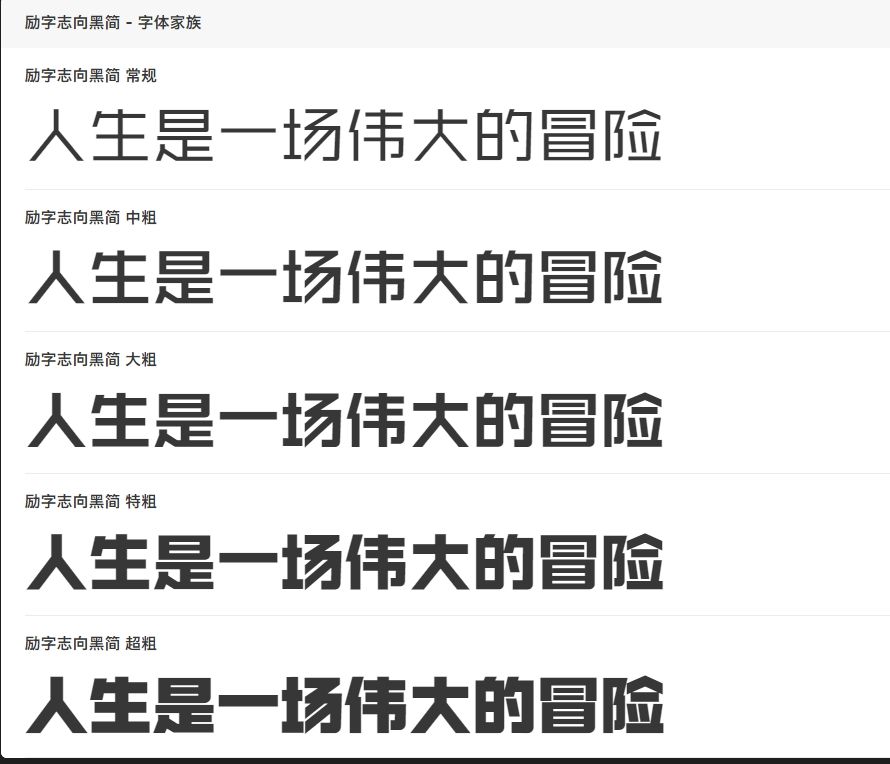
探索字体之美,几款创意无限的个性字体!
在数字化时代,字体设计已成为展示个性与创意的重要方式。字体不仅是文字的呈现方式,更是表达情感和传递信息的工具。今天,就让我们一起来探索几款创意无限的个性字体,感受它们带来的独特魅力。
首先推荐的是手写字体——MyFont濑户风车简。这种字体仿佛是由画笔亲手绘制而成,线条流畅、自然,充满了艺术感。无论是用于海报设计、广告宣传还是个人签名,手绘风字体都能展现出一种独特的个性和创意。
另一款值得推荐的字体是“科技风字体——励字志向黑”。它简洁明了、线条硬朗,给人一种现代感和科技感。在科技、互联网等领域,使用科技风字体能够凸显出专业性和前沿性,让信息更加易于理解和接受。
此外,“复古风字体——励字舒体简繁”也是一款备受欢迎的字体。它带有一种怀旧和复古的气息,仿佛让人回到了过去。在文艺、复古风格的设计中,复古风字体能够增添一份独特的韵味和情感。
这些个性字体各具特色,能够满足不同场合和需求。无论是追求艺术感的手绘风字体,还是展现专业性的科技风字体,亦或是充满怀旧气息的复古风字体,它们都能为文字和设计增添一份独特的魅力和个性。
在字体设计日益多样化的今天,我们不妨多尝试一些新的字体,让文字和设计更加生动有趣。相信这些创意无限的个性字体,一定能为你带来全新的视觉体验。